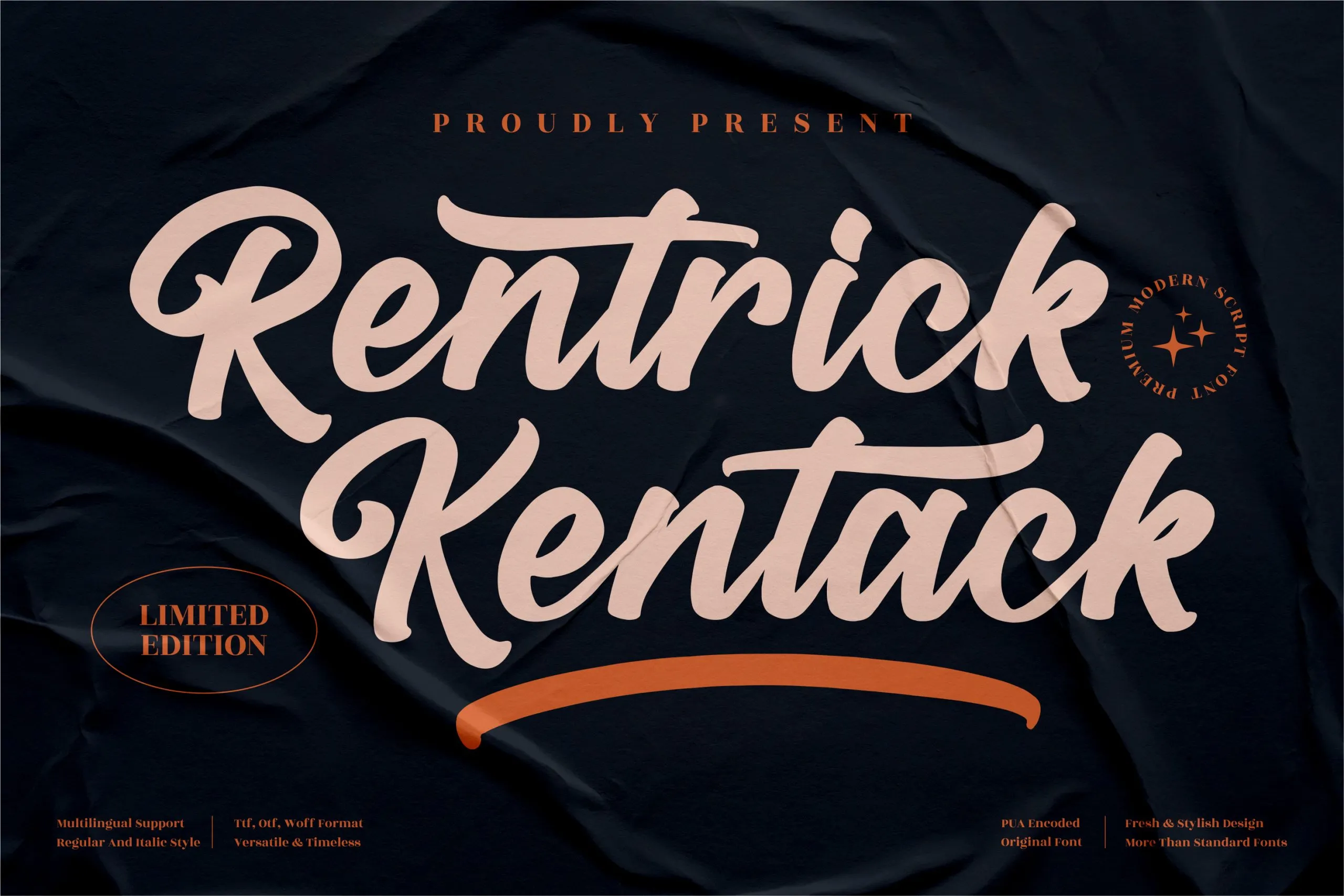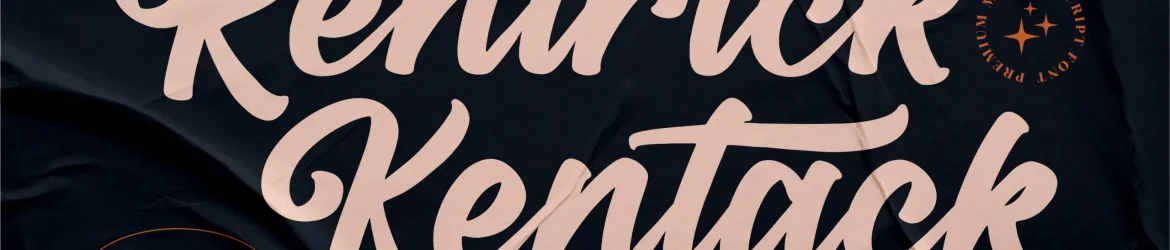
A Rentrick Kentack Font é uma elegante tipografia de calligrafia moderna criada pelo estúdio Perspectype Studio. Com seu design clean e sofisticado, esta fonte premium se destaca para projetos de nível superior como logotipos, marcas de marca, designs para móveis domésticos, embalagens de produtos, taças, mensagens, cartazes, sacolas de compras, camisetas personalizadas, capas de livros, cartões de nome, cartões de convite, cartões de cumprimento e etiquetas. Suas linhas finas e elegantes garantem um acabamento sofisticado em praticamente qualquer projeto que você possa imaginar. Seja para decorar uma embalagem gourmet ou criar o design perfeito do seu site personalizado, a Rentrick Kentack Font se destacará como um elemento de alta qualidade. Apreciadores de design e criativos desse gênero encontrarão sua fonte ideal para transformar qualquer projeto em algo realmente especial.